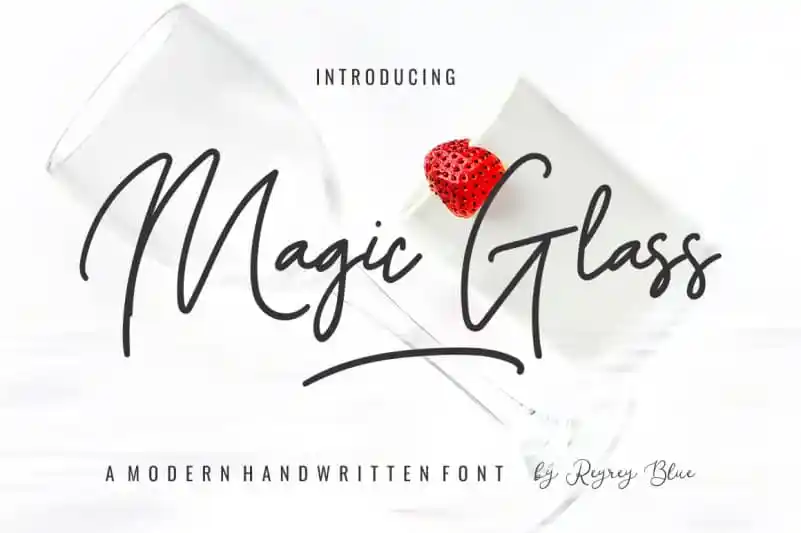
Magic Glass é uma fonte escrita à mão que traz a essência autêntica e charmosa do estilo da caligrafia com uma pegada atual e fresca, ideal para aqueles que desejam dar um toque único e elegante aos seus projetos digitais. Desenhada meticulosamente pela ReyreyBlue, essa fonte escrita à mão não apenas preserva os atributos clássicos da caligrafia, mas também traz uma sensação de modernidade e originalidade que a torna irresistível para designers e criadores de conteúdo. Adotar Magic Glass na sua próxima criação digital pode transformar seus trabalhos em algo realmente memorável e único, elevando seu design ao próximo nível. Não hesite em explorar a possibilidade de incorporar essa fonte à sua lista de favoritos.